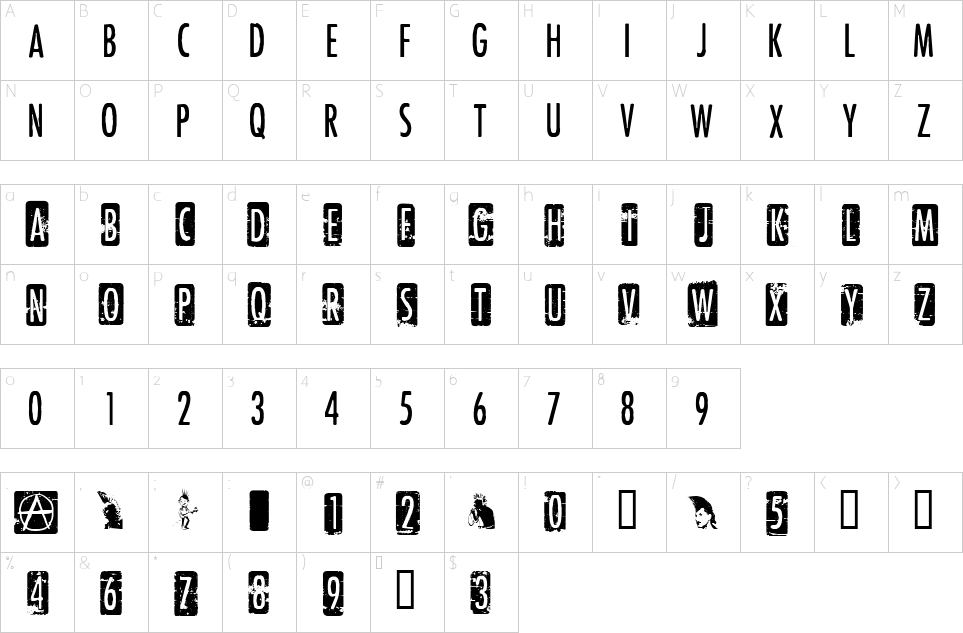
Aqui está uma descrição em português do Brasil para a página de download da fonte ‘Punk Rock Show Font | 1001 Free Fonts’, baseada na descrição original fornecida: Punk Rock Show é uma fonte elegante e desconcertante, perfeita para quem busca um estilo alternativo e vibrante para seus projetos digitais. Escrevendo com essa fonte, você conseguirá dar um toque único e divertido a seus textos. CloutierFontes concebeu Punk Rock Show, e ele tem sido baixado milhares de vezes, demonstrando a sua popularidade entre designers de todo o mundo. Esta fonte é uma excelente opção para quem está procurando uma maneira criativa de decorar seus materiais de negócios, como cartazes, flyers ou websites. Ela também é perfeita para quem deseja dar um tom mais moderno à sua página de blog ou site pessoal. A Punk Rock Show é uma fonte versátil que combina uma aparência minimalista com um ar de energia underground, tornando-a um recurso gráfico essencial para qualquer designer.